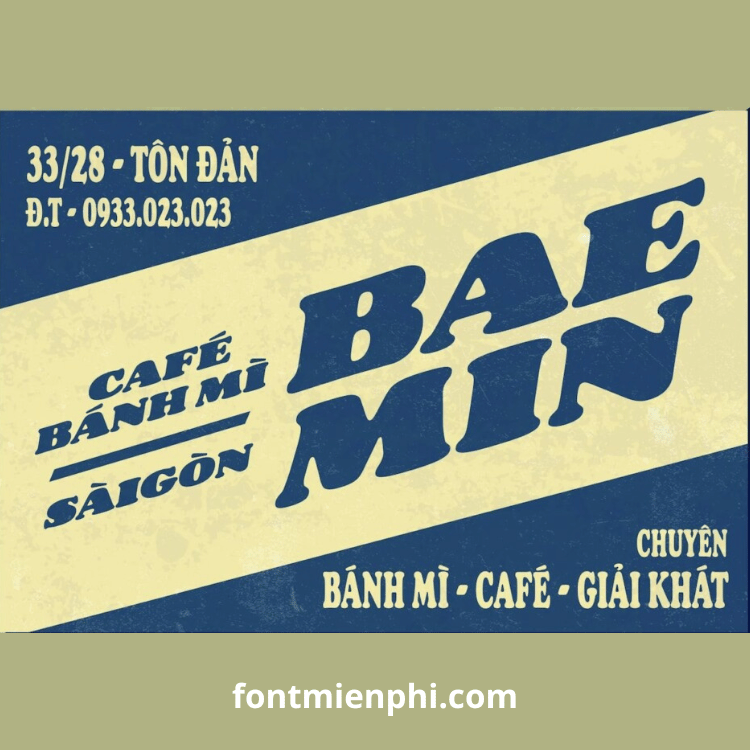
Font BM Lucas Việt hóa , Font mới từ BAEMIN
Font BM Lucas Việt Hóa – Kiểu Chữ Độc Đáo Đến Từ Thương Hiệu BAEMIN
Giới thiệu nổi bật:
BM Lucas là font chữ việt hóa độc quyền từ thương hiệu giao đồ ăn nổi tiếng BAEMIN, mang đến làn gió mới cho thiết kế đồ họa với phong cách hiện đại và trẻ trung. Font chữ này đặc biệt phù hợp cho các dự án liên quan đến ẩm thực, công nghệ và thương hiệu hướng đến giới trẻ.
Đặc điểm ấn tượng:
• � Thiết kế độc đáo kết hợp nét thanh-mảnh cân đối
• ✅ Hỗ trợ đầy đủ tiếng Việt với bộ dấu chuẩn
•  2 phiên bản chính (Regular và Bold) đáp ứng đa dạng nhu cầu
•  Tối ưu cho digital – hiển thị đẹp trên mọi nền tảng số
Ứng dụng đa dạng:
• Thiết kế app giao đồ ăn, ứng dụng công nghệ
• Banner quảng cáo digital marketing
• Bao bì sản phẩm F&B
• Ấn phẩm truyền thông thương hiệu trẻ
BM Lucas – Lựa chọn hoàn hảo cho các thương hiệu muốn thể hiện sự năng động và hiện đại!